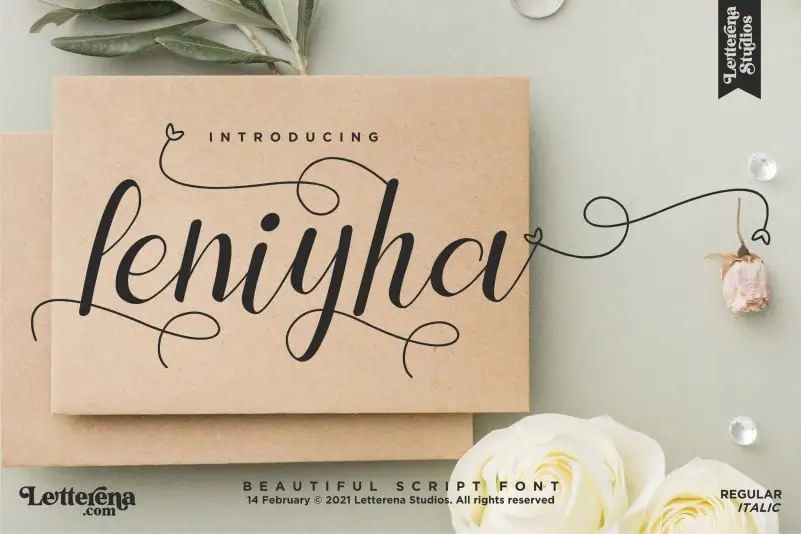
Leniyha Script Font – Download Grátis
A Leniyha Script é uma elegante fonte de escrita cursiva, criada pelo designer Letterenastudios, perfeitamente adaptável para diversos projetos. Esta fonte romântica encaixa-se aperfeiçoadamente em estilos como logotipos e identidades corporativas, designs de móveis, embalagens de produtos, tigelas personalizadas, frases motivacionais, painéis de propaganda, sacolas de shopping, camisetas personalizadas, capas de livros, cartões de convite, cartões de felicitações e etiquetas. Além disso, a Leniyha Script é perfeita para gráficos fotografados, marca d’água especial, eventos especiais e qualquer outra tarefa gráfica que você possa imaginar precisando de um toque elegante e sofisticado da escrita cursiva. Com sua Linienha Script Font, deixe seu projeto brilhar com uma sensação única e envolvente.